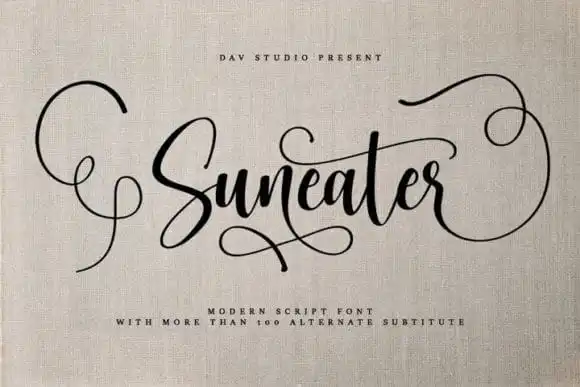
Suneater Calligraphy Font – Download Grátis
A fonte Suneater Calligraphy é uma delícia para quem busca elegância e sofisticação no design. Desenvolvida pelo estúdio Dav Studio, ela oferece um aspecto autêntico e suave de escrita a mão. Com seu formato PUA encoded, você pode facilmente acessar todos os caracteres e swashes da fonte. Perfeito para criar cartões de convite encantadores, arte de postais delicados, posts sociais impecáveis e cartas de saudações adoráveis, Suneater Calligraphy é a escolha perfeita para projetos que exibem estilo e naturalidade. Suave e suculenta como ela só pode ser em uma fonte a mão escrita, essa fonte é certamente um item indispensável para qualquer coletânea de fontes.